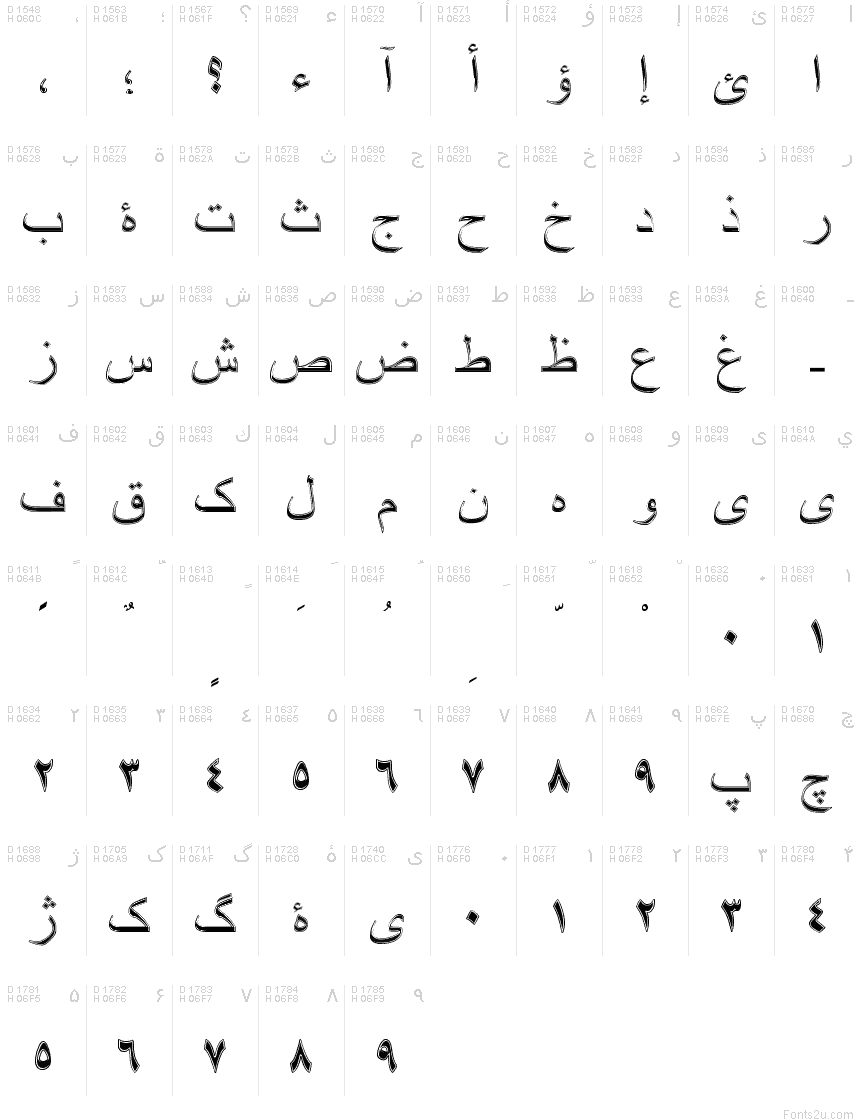
B Sara to bezpłatny krój pisma arabskiego autorstwa Borna Rayaneh, wyróżniający się miękkim, kaligraficznym stylem, który bardziej przypomina pismo odręczne niż formalną typografię. Litery bazują na zaokrąglonych pociągnięciach, łagodnych łączeniach i zwartych sylwetkach, co nadaje całości spokojny, płynny rytm, unikając przy tym ostrych kontrastów czy sztywnej geometrii.
Doskonale sprawdza się na plakatach kulturalnych, okładkach książek, kartkach okolicznościowych, opakowaniach i w krótkich hasłach brandingowych, gdzie darmowy krój ma zapewnić ciepły, osobisty charakter. Wykorzystaj go w nagłówkach, tytułach lub krótkich cytatach, jeśli szukasz arabskiego pisma, które jest przyjazne i spójne, a jego krzywizny sprawiają, że słowa wyglądają na naturalnie połączone.